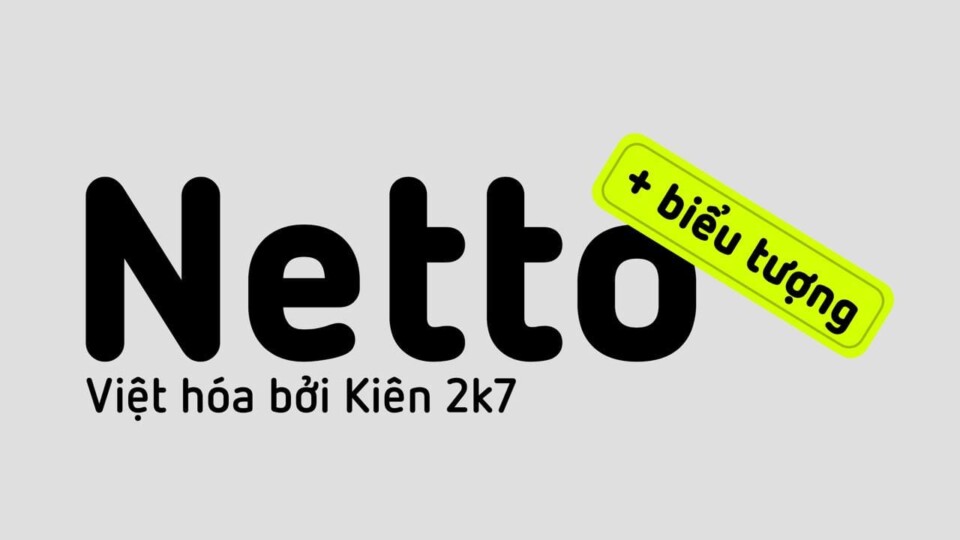
Trong thế giới đồ họa hiện đại, việc tìm kiếm một bộ Font Việt hóa Netto chất lượng là ưu tiên hàng đầu của nhiều nhà thiết kế. Đây là một bộ Font Chữ mang phong cách sans-serif hiện đại, nổi bật với các đường nét bo tròn tinh tế và cấu trúc hình học gãy gọn. Netto không chỉ mang lại cảm giác thân thiện, gần gũi mà còn đảm bảo tính chuyên nghiệp cao trong mọi sản phẩm truyền thông. Phiên bản Việt hóa giúp người dùng dễ dàng ứng dụng vào các văn bản tiếng Việt mà không lo lỗi hiển thị dấu.
Ưu điểm vượt trội của Font Việt hóa Netto
Thiết kế tối giản và hiện đại
Bộ Font Việt hóa Netto được đánh giá cao nhờ sự đơn giản nhưng không kém phần sang trọng. Các ký tự được tối ưu hóa khoảng cách, giúp người xem dễ đọc ngay cả ở kích thước nhỏ. Điều này khiến nó trở thành lựa chọn lý tưởng cho các bạn học sinh làm báo cáo hoặc giáo viên thiết kế bài giảng điện tử sinh động.
Tính ứng dụng linh hoạt trong đời sống
Bạn có thể sử dụng Font Việt hóa Netto cho nhiều mục đích khác nhau như thiết kế logo, làm tiêu đề video, hay trình bày các ấn phẩm học đường. Sự đa dạng trong các biến thể từ mỏng đến đậm giúp người dùng linh hoạt trong việc phân cấp thông tin, tạo điểm nhấn thị giác mạnh mẽ cho người xem ngay từ cái nhìn đầu tiên.
Cách sử dụng Font Việt hóa Netto hiệu quả